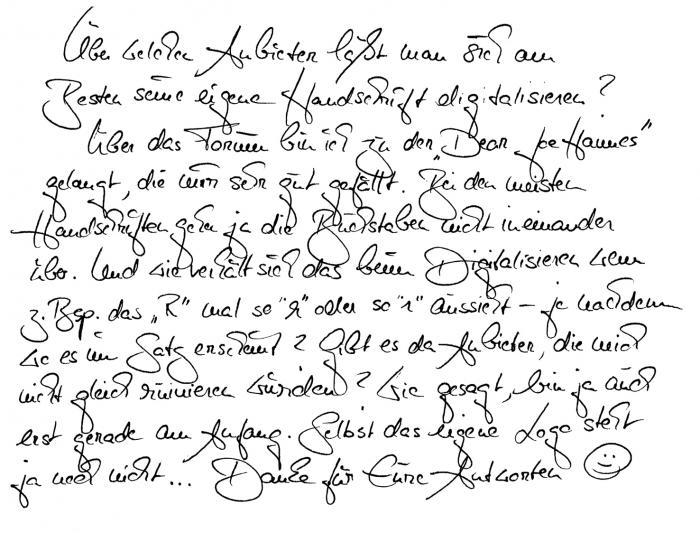
Anbieter zum Digitalisieren von Handschriften
Im Zuge der Entwicklung meines eigenen Erscheinungsbildes bin ich auf der Suche nach einem Anbieter, der Handschriften in digitale Schriften erstellt.
Wer hat Erfahrungen damit und könnte mir Tipps geben?
Klingt spitze - ist leider nur nicht in meinem Budget. Mist. Dann halt brav weiter das in Vektoren umwandeln was ich brauche....
das, was dort schon jenseits deines Budgets ist, ist dann aber auch nur ein grundlegender Zeichensatz, in dem jeder einzelne Buchstabe genau einmal drin vorkommt, also nur ein A, nur ein B und nur C... was du dir aber vorstellst, ist von jedem Buchstaben aber eine größere Anzahl, die dann kontextabhängig über OpenType-Funktionen gesetzt werden. Dabei kommen dann leicht einige 1000 unterschiedliche Buchstaben zusammen, die jeder einzelne in einem Grafikprogramm von Hand nachgezeichnet werden müssen, um dann in einem Font zusammengeführt, ausgerichtet und angeglichen werden müssen, dass dann die Buchstabenverbindungen hinterher auch funktionieren. Hinzu kommt, dass man sich dann über die Programmierung der automatischen Ersetzung durch die OpenType-Tables her machen muss, damit die Schrift dann hinterher tatsächlich wie eine Handschrift aussieht. Gerade bei deiner Handschrift, die teils verbunden und teils aus einzelnen Buchstaben besteht ist da einiges an Programmierung erforderlich. Du wirst also kaum jemanden finden, der dir in dein Budget passend daraus eine komplette und wirklich wie deine Handschrift aussehende Schriftart zusammenbaut.
Es ist ja nicht so, dass mir deine Anschrift nicht gefällt, aber sie ist eben nicht so besonders gut geeignet um daraus einen guten Schreibwarencomputer von zu bauen, dass sie eben sehr lebendig ist. Schau dir nur mal deine Buchstaben an, nicht nur das r sieht jedes Mal anders aus, je nachdem wo im Wort es steht, sondern das trifft praktisch auf jeden Buchstaben zu. Und nur durch diesen Wandel der Formen hast Du diesen Handschriftcharakter. Das was dir dort aber für 1200 € angeboten wird, sind gerade einmal Buchstaben von A bis Z in Groß- und Kleinbuchtstaben, sowie Zahlen und Satzzeichen. Das eignet sich dann nur für eine Schrift mit einer so großen Gleichförmigkeit das dann so etwas ähnliches wie Comic Sans dabei heraus kommt.
Ich selbst hatte mal einen solchen Menschen kennen gelernt, dessen Handschrift wirklich wie gedruckt aussah. Bei dem wäre es ein Leichtes gewesen, von seiner Handschrift einen Computerfont zu erstellen. Er schrieb jeden Buchstaben einzelnen und so akkurat, als hätte er eine Schablone benutzt.
Also bleibt die wahrscheinlich nur eines: Entweder du gibst dieses Projekt auf oder du schaffst dir selbst die dazu nötige Software an (welche es zum Beispiel für Linux auch ganz umsonst gibt, dort nennt sich das Programm FontForge) arbeitest dich dort ein, und machst dich dann selber an die Arbeit, immer wenn du etwas Zeit dazu findest. Ich glaube aber das wird ein ziemlich langer Weg werden, bis Du deine Handschrift in eine wirklich sauber nutzbare Computerschriftart übersetzt hast.
Ich bin mir dann ziemlich sicher, dass du selbst den genannten Preis für diese Minimalhandschrift als nicht mehr zu teuer empfinden wirst.
Ich nehme mal an, du willst nicht ganze Texte aus deiner Handschrift setzen, sondern nur Headlines oder ähnliches?! Und in dem Fall würde ich – unabhängig davon, ob deine Handschrift gut digitalisiert werden kann oder nicht – die Variante Schreiben–Scannen–Vektorisieren bevorzugen, weil, glaube ich, keine digitale Schrift die feinen Buchstabenunterschiede so genau abbilden kann, wie es deiner Hand beim Schreiben „passiert“. Auch die Schriftlinie und die Ausrichtung und Schreibgeschwindigkeit spielen ja eine Rolle und können zur Gestaltung beitragen. Was ist zum Beispiel, wenn du eine Aussage (im Wortsinn) unterstreichen willst, dann musst du eine Linie dazubasteln, wenn du alles mit der Hand schreibst, geht das aus dem gleichen Fluss. Oder was, wenn du bei der Gestaltung für eine fragende Aussage ein ganz besonders großes Fragezeichen willst, dann ist ein Font auch schon wieder nicht flexibel genug. Und so Beispiele lassen sich bestimmt noch mehr finden …
Du kannst ja mal durchrechnen, wie viele Schriftzüge du für den Preis eines (unflexibleren) Fonts selbst digitalisieren kannst ehe letzterer sich amortisiert, wenn du deinen eigenen Stundensatz ansetzt – kannst dir ja auch nen Freundschaftspreis machen ;-)
Nun, je nach Ansprüchen gibt es aber auch eine komplett kostenlose Lösung: MyScriptFont.
Hier muss man ein Formular ausfüllen, einscannen und bekommt davon dann einen Font, den man ja dann ja in einem Font-Bearbeitungsprogramm nachbearbeiten. So für mal ne persönliche Headling könnte das wohl auch gehen.
Myscriptfont hatte Vitrioloel oben ja schon genannt ... und ich habe diesen Dienst auch schon genutzt* – und mit dem so erstellten Font tatsächlich überraschend gut arbeiten können. Aber das sieht nur bis, sagen wir mal, 24 pt gut aus. Darüber hinaus (sofern man nicht nachbearbeitet, was ich nicht konnte und wollte) wird’s dann grobmotorisch.
*) Dazu habe ich Buchstaben en masse geschrieben, gescannt und dann das Formular in Photoshop »ausgefüllt« um harmonischere Formen hinzubekommen.
Nachtrag: Ich hatte es damals auch bei paintfont.com versucht, zumal es da die Möglichkeit der individuellen Glyphenauswahl (und damit mehrseitige »Templates«) gibt – dann klappte aber das Hochladen leider nie (4 Versuche mit unterschiedlich aufbereiteten Daten), weil angeblich der »Scan« zu schlecht war (dabei hatte ich das Template-PDF im Photoshop geöffnet und bestückt). Ich hatte mir damals auch noch ein Raster von yourfonts.com runtergeladen, weiß aber nicht mehr so recht, warum ich mich dagegen entschieden habe – hatte wahrscheinlich eher was mit den AGB als mit der Qualität zu tun, denn ich hab nicht mal einen Test gefahren.